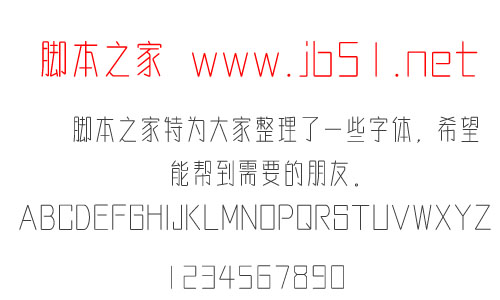
劉兵克曦冉體字體是由站酷原創(chuàng)作者劉兵克創(chuàng)作的一款設計優(yōu)美、風格簡約的藝術字體,,字形修長,線條纖細干凈,整體設計有創(chuàng)意,用作美術字體非常棒,特點鮮明,適用于各類時尚品牌的廣告設計與包裝。但是辨識度較低,不適合用于排版印刷,歡迎喜歡劉兵克曦冉體的朋友前來下載使用。